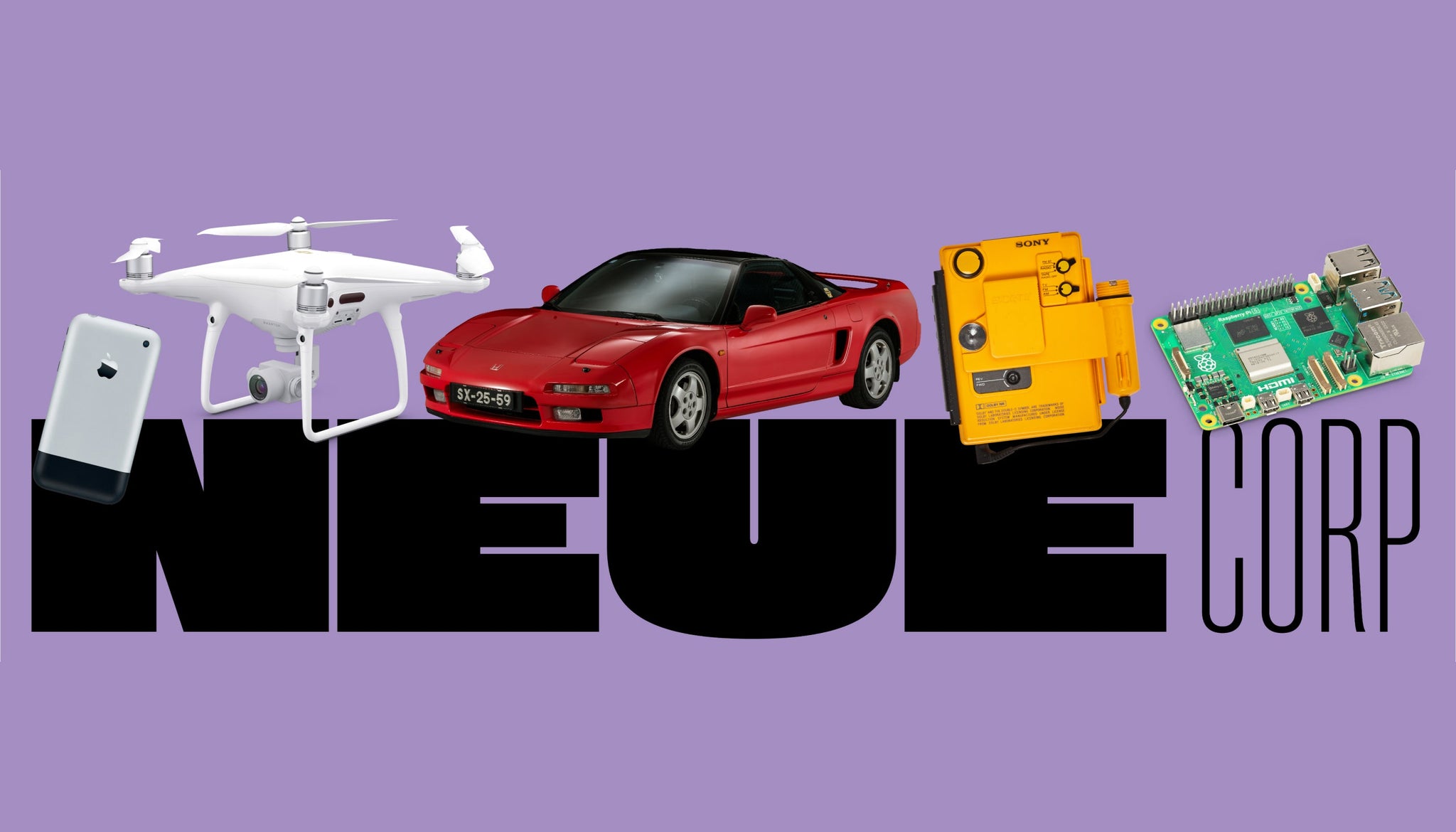
Neue Corp , la dernière version de Pangram Pangram, est une police de caractères qui est avant tout polyvalente.
Née de l'amour et de la combinaison d'influences typographiques classiques, à travers le prisme des technologies typographiques contemporaines, Neue Corp s'adapte à tous les scénarios créatifs. Des titres audacieux et expressifs aux corps de texte raffinés et lisibles, Neue Corp propose une large gamme de graisses, de largeurs et de variations stylistiques.
Tirant ses racines à la fois de l'excentricité des vieux caractères en bois et de la précision des néo-grotesques, Neue Corp est le genre de police qui non seulement s'adapte à différents contextes, mais qui s'y épanouit pleinement. Pour célébrer sa flexibilité, nous nous sommes penchés sur les éléments qui font une bonne association de polices avec Neue Corp , et la réponse est : elle-même. Après tout, il y a de quoi faire. Que vous travailliez sur un projet physique, numérique, éditorial ou d'identité, ces associations constituent au moins un tremplin vers l'offre apparemment infinie de Neue Corp.
Extended Bold et Compressed Light
Cette association est une question d'équilibre. Le gras Extended apporte une présence ample et assurée, parfaite pour affirmer son style. Ses proportions généreuses et son poids élevé attirent immédiatement l'attention, tandis que le léger comprimé contrebalance sa forme Narrowet délicate. Ensemble, ils s'intègrent parfaitement dans les pages éditoriales, avec des titres percutants associés à des détails plus légers et élégants qui guident le lecteur.
Narrow Bold et Extended Thin
Le Narrow Bold est incroyablement polyvalent. Sa forme plus fine lui confère une lisibilité supérieure tout en offrant suffisamment de présence pour se démarquer. Associé au Extended Thin, aéré et raffiné, il offre une esthétique plus moderne et équilibrée, à l'allure minimaliste et aérienne. Le poids du Bold ancre le design, tandis que la largeur du Thin apporte une touche d'élégance, rendant cette association parfaite pour tout contexte privilégiant la clarté et le style.
Condensed Black et Wide Thin
Le Black Condensed offre une intensité saisissante, contrastant avec la légèreté et l'ouverture du Thin Wide. Cette association apporte une touche d'intensité à toute application où l'on souhaite allier puissance et prouesse. Il faut dire que le Black Condensed affiche une audace affirmée, tandis que le Thin Wide offre un contrepoint élégant, conservant un design solide et équilibré malgré des poids et des largeurs extrêmes.
Condensed Black et Wide Regular
Le Noir Condensed est intense, compact et idéal pour transmettre un message puissant dans un espace restreint. Associé au Large Régulier, il crée un contraste saisissant, à la fois terre-à-terre et ouvert. Les proportions généreuses du Large Régulier apportent une touche de fraîcheur au sein du Noir Condensed dense, offrant un rendu harmonieux et captivant.
Compressed Bold et Normal Regular
Avec Compressed Bold, vous obtenez un style compact qui fait forte impression dans un format compact. Normal Regular complète ce style avec une structure verticale plus traditionnelle qui stabilise le design, ajoutant une touche de fiabilité sans sacrifier le style.
Au final, Neue Corp prouve que parfois, la meilleure association est l'absence d'association. Il s'agit plutôt d'une combinaison judicieuse de sa vaste gamme de graisses, de largeurs et de styles. Du contraste saisissant de l'Extended Bold avec le Compressed Light à l'élégance discrète du Narrow Bold et de l'Extended Thin, Neue Corp s'adapte sans effort à tous les styles. C'est une police d'une flexibilité infinie, qui permet de jouer sur les nuances, quel que soit le contexte.